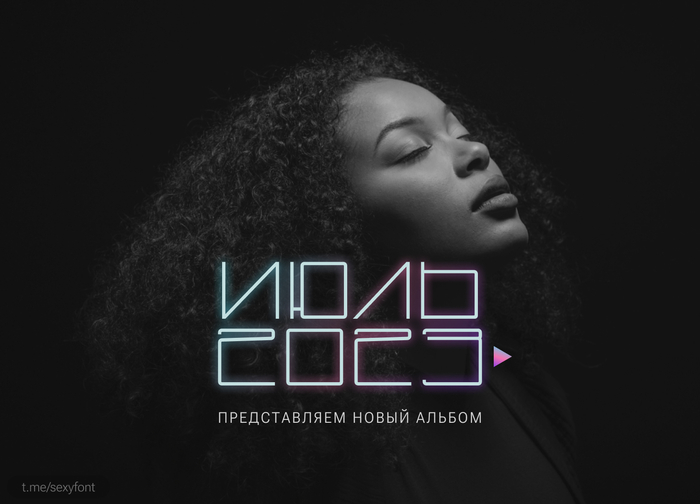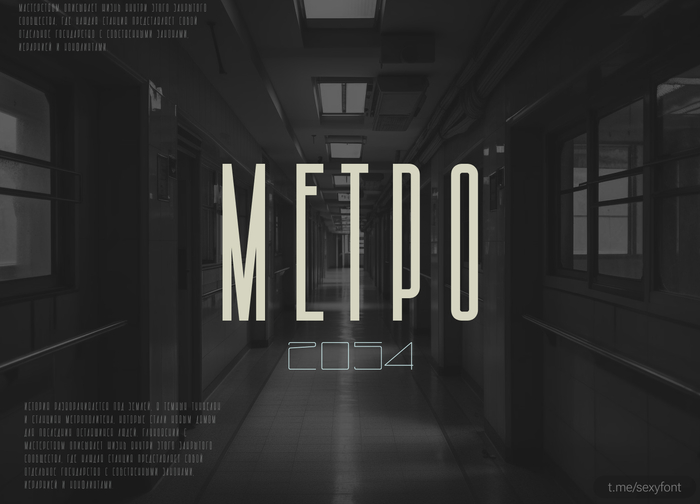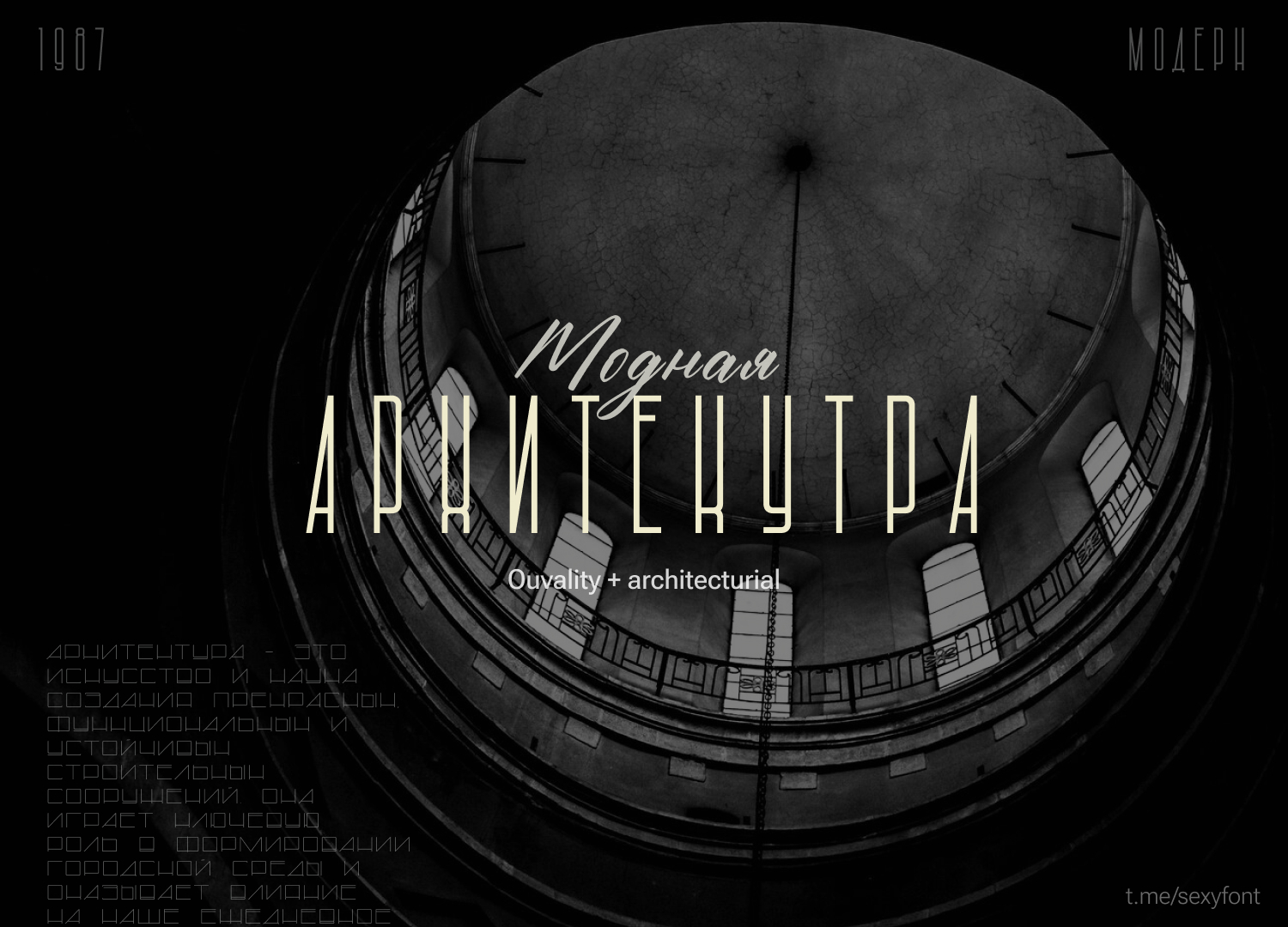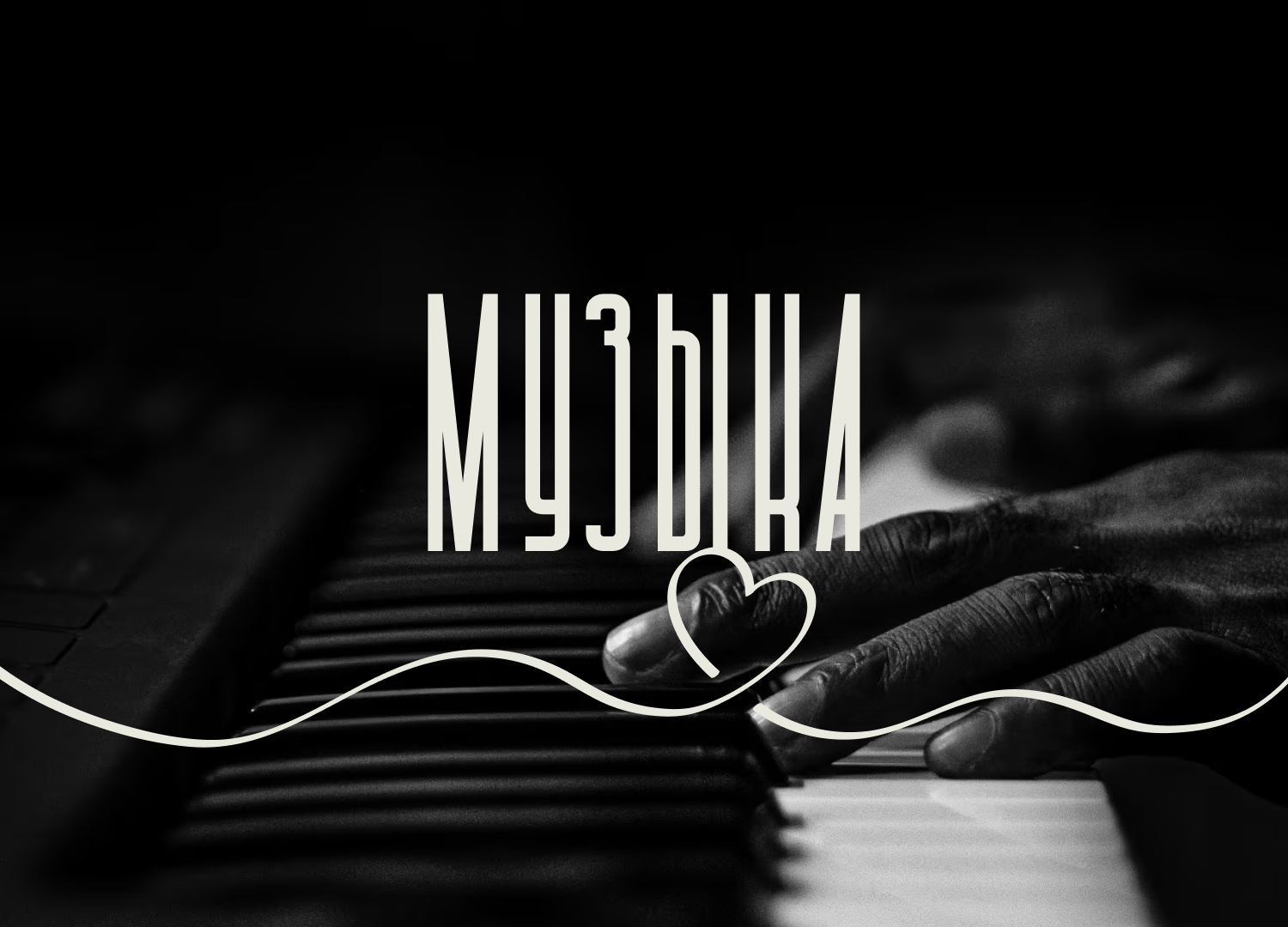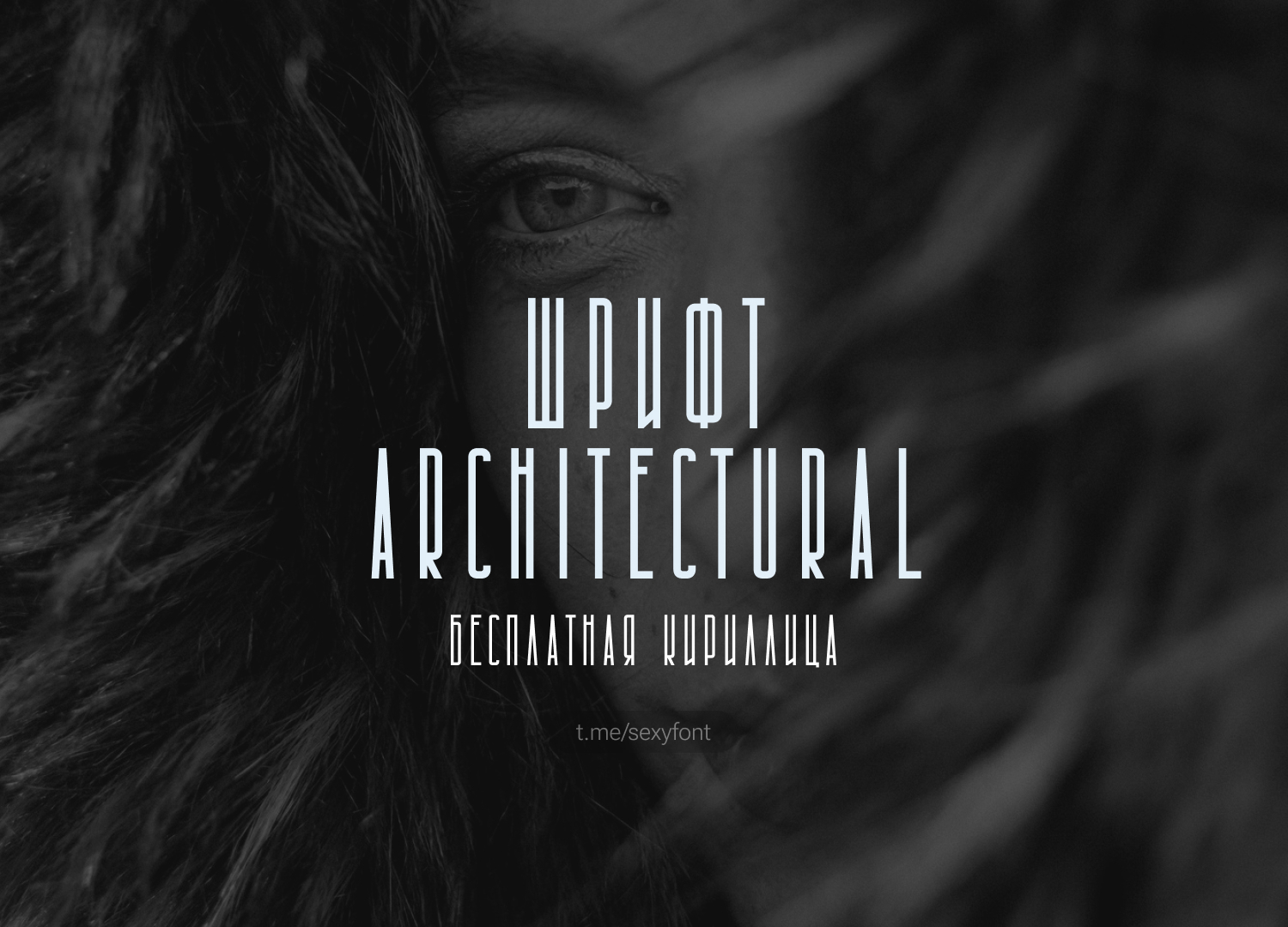
Высоченный шрифт Architectural
Читаемость конечно на грани, но все же для каких-нибудь коротких декоративных надписей подойдет) Не так уж много у нас высоких и компактных шрифтов. А еще у него есть много начертаний и вариативность) Можно настраивать как ширину букв, так и толщину.